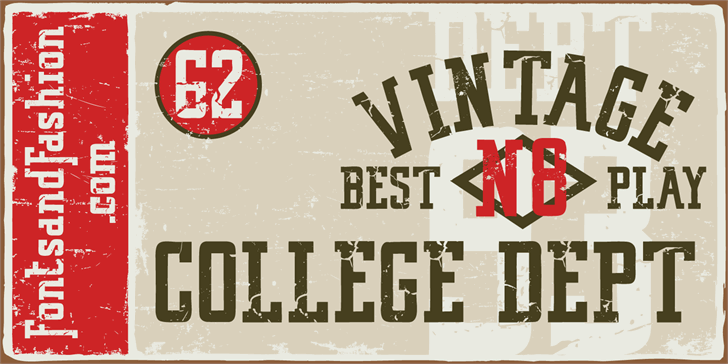
VINTAGE COLLEGE DEPT_worn font – Download Grátis
A fonte ‘VINTAGE COLLEGE DEPT_worn’ é uma escolha perfeita para projetos de design moderno e sofisticado que valorizam o passado. Criada por Hamilton em 2014, esta slab serif é perfeitamente adaptável para aplicativos como cartões de crédito personalizados, menus de restaurantes antigos ou até mesmo anúncios históricos. Seu estilo rústico e vintage adiciona um toque autêntico e aconchegante aos textos mais modernos. Para aqueles que buscam uma fonte para trabalhos profissionais, o ‘VINTAGE COLLEGE DEPT_worn’ oferece tanto elegância quanto personalidade. Acesso completo à esta obra de arte tipográfica pode ser obtido através do site Fontsandfashion.com, onde também encontrará diversas outras fontes únicas e inspiradoras para sua coleção. Para quem gosta da ideia, não se esqueça de acompanhar a Fontsandfashion nas redes sociais. Acesse o Facebook e o Pinterest para explorar ainda mais desenhos artísticos e tipográficos que podem tornar seus projetos ainda mais incríveis. Se você já é um assinante do Fontspace, certamente terá uma conexão natural com essa fonte, e os demais recursos de design disponíveis lá são semelhantes em qualidade e riqueza.